今回は、輪郭(アウトライン)のデザインがユニークな日本語フリーフォントをまとめてご紹介します。
ちょっとクセのある輪郭や、印象的なラインが特徴のフォントは、文字そのものに表情を与えたり、物語性を演出したいときにぴったりです。使い方次第で、ぐっと雰囲気のあるデザインに仕上げることができます。
そんな「輪郭に個性が光る」フリーフォントに焦点をあてて、フォントをご紹介していきます。
輪郭(アウトライン)がユニークに作られているおすすめの日本語フリーフォント
以下のサンプル画像は本記事で紹介している一部ですが、輪郭が印象的に作られているため、そのまま使うだけでも雰囲気がでるので、タイトルやキャッチコピーなどにもぴったりなフォントばかりです。
雨墨ゴシック
雨墨ゴシックフォントは輪郭をギザギザな滲んだ質感を感じるゴシック体フォントです。
イモケンピ
FZイモケンピフォントは、輪郭がギザギザな加工が施されているユニークなフォントです。
柊の葉っぱ
柊の葉っぱフォントは、「柊の葉」をイメージして作られたトゲトゲした輪郭が特徴的なデザインフォントです。
継ぎ接ぎぱっち
継ぎ接ぎぱっちフォントは、 さまざまな柄が組み合わったパッチワークのように構成されているデザインフォントです。
瀞ノグリッチ
瀞ノグリッチ明朝フォントは、源ノ角をベース、グリッチノイズなエフェクトが施されているフォントです。明朝体ベースの「瀞ノグリッチ明朝体」とゴシック体ベースの「瀞ノグリッチ黒体」が用意されています。
ヒカリノカナ荒
FGPヒカリノカナ荒フォントは、上下に飛びているユニークな動きがある半角カナ文字のようなフォントです。
文字の輪郭がジャギジャギとした加工が施されていることで、滲んだような質感があるデザインとなっています。
濃淡ゴシック
濃淡ゴシックは、オープンソースフォントの「LINE Seed JP」をベースに、ペンで塗りつぶしたような質感や輪郭をもつフォントです。
可愛いデザインとの相性はもちろん、少しインパクトを出したいときに取り入れても良さそうです。
異世明/異世ゴ
異世明・異世ゴフォントは、異世界に転移(ワープ)するときに「ぐにゃ」っと歪むような質感がほどこされているデザインのインパクトあるフォントです。
零ゴシック
零ゴシックフォントは、ガラスのように割れている質感やヒビが入っているようなユニークな加工が施されてるフォントです。
質感がしっかり入っているので、ベタ打ちするだけでも迫力がでるフォントです。
源界明朝
源界明朝フォントは、読める限界ギリギリまで破壊されたようなかすれたグランジ質感が施されているデザインフォントです。
クラフト明朝
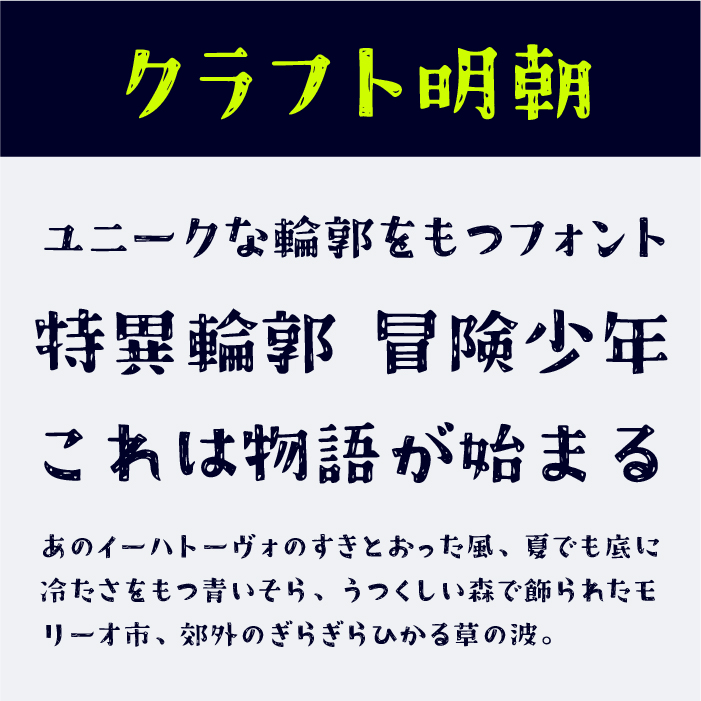
クラフト明朝フォントは、手書きペンでグシャグシャに塗りつぶしたかすれがあるユニークなデザイン系明朝体です。
破線G
破線Gフォントは、「源ノ角ゴシック」フォントをベースにして、アウトラインを破線で表現したステッチやミシン目のような点線になっているユニークなフォントです。
瞬きノ明朝
瞬きノ明朝フォントは、文字がギザギザに揺れているようなユニークな加工が施されているインパクトあり、爽やかさを感じるデザイン明朝体フォントです。
ボトムズ
ボトムズフォントは、ドロっと液体が溶け出したような沼の底のようなテクスチャを加えて制作されたデザインフォントです。